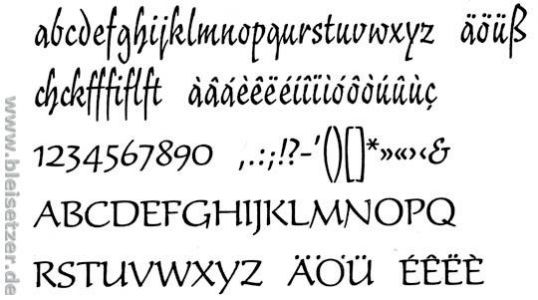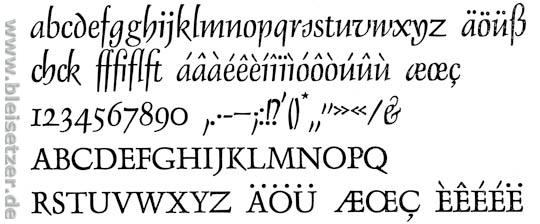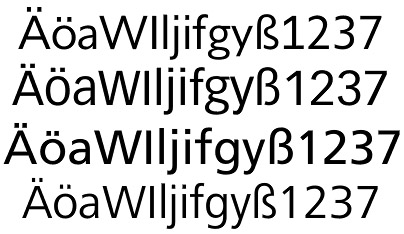
Schriftklau beim Design
Ich hatte erst überlegt, mich im Schriftpiraterie-Thread zu beteiligen, aber dieser Aspekt verdient meiner Meinung nach einen eigenen Thread. Es geht mir darum, dass viele Schriftarten offensichtlich direkt von einer anderen Schriftart abgeleitet sind, und ihr nicht etwa nur zufällig ähnlich sehen. Leicht verändert werden sie dann als neues Produkt deklariert. Ich möchte nur mal ein paar zufällig herausgesuchte Beispiele nennen (es gibt sie zuhauf):
Envoy (Minion)
Tyrnavia (Janson)
Gf H2O (Frutiger)
Bei anderen Shops findet man sicherlich ähnliche Beispiele.
Unter den Beispielen können natürlich hin und wieder welche sein, die nur unter anderem Namen vertrieben werden (wie Nimbus Sans für Helvetica). Die Segoe ist da wohl nur so umstritten, weil sie eben durch ihre Verwendung herausragt. Ansonsten scheint mir so etwas hundert-, wenn nicht tausendfach betrieben zu werden.
Bei diesem Thema bitte sehr, sehr vorsichtig sein! Die Beispiele sind nicht gut.
Allzu oft wird schnell gesagt, der hat mein Design, meine Idee "geklaut". Besser wäre wohl, dieser oder jener hat ebenfalls den selben Ansatz aufgegriffen bzw. weiterentwicklet bzw. seine Interpretation angefertigt. Alle Schriftentwerfer stehen auf den Schultern der Ahnen. Ein neues Design kann nur 25 Jahre geschützt werden, und zwar als Geschmacksmuster beim Patentamt. Von der praktischen Druchsetzbarkeit brauchen wir nicht zu sprechen, die geht fast gegen Null.
Es steht also jedem frei eine neue Version einer älteren oder gar historischen Schrift wie Janson, Kiss, Garamond und Co. zu versuchen, solange man keine schon digitale Schrift als Grundlage nutzt, also alles selber zeichnet.
Es ist schon merkwürdig wieviele Entwerfer (GGL, Spiekermann, Karl Heinz Lange, Georg Salden, Weidemann) in der einen oder anderen Situation freimütig damit koketieren, daß dieser oder jener ihrer verehrten Kollegen "ihre" Idee benutzt hätten. Das scheint zum etablierten Standesgeklapper zu gehören. :-)
Vom Schriftenklau im eigentlichen Sinne können wir sprechen, wenn große Firmen schon digitale Schriften nutzen und diese geringfügig abändern und das gar nicht einmal mit viel Mühe und dieses als "ihre Hausschrift" vorstellen um die Lizenzgebühren zu sparen. Die bekannten Fälle kann jeder auf Typophil oder im Fontblog nachlesen. Und trotz Offensichtlichkeit und öffentlicher Brandmarkung beleiben diese Dinge oftmals ungestraft, da diese Firmen einfach zu groß sind. Yves Peters hat sich auf dieses Gebiet spezialisiert und sammelt solche Fälle.
Von "Innovation" war hier nicht die Rede, sondern von Diebstahl! Ein Produkt muß nicht innovativ sein, um erfolgreich zu sein. Oftmals sind es nicht die Pioniere, die den Erfolg einstreichen, sondern die Nachfolger.
Futura ist kein gutes Beispiel, es war wohl die einzige Schrift die gerichtlich als Kunstwerk eingestuft wurde. Aber da müßte ich noch einmal nachlesen.
Nehmen wir mal eine andere Schrift, die Kabel von Rudolf Koch zum Beispiel. Wirklich jeder kann heute seine eigene Version davon erstellen und anbieten, solange er keine fremden Vorlagen nutzt und alles selber zeichnet und solange er keine Markenrechte, in dem Fall die Marke "Kabel" verletzt. Dies ist völlig legitim und rechtlich ok.
Die Moral lasse ich hier mal außen vor, das ist ein anderes, wenn nicht minder wichtiges Feld. Mein Tip: Bitte keine Schriften von noch lebenden Personen ohne deren schriftliche Einwilligung antasten. Ansonsten kann man vieles probieren, sollte sich aber immer seiner Verantwortung bewußt sein und sein Können richtig einschätzen. Sonst fällt es nur negativ auf die eigene Person zurück.
Es steht also jedem frei eine neue Version einer älteren oder gar historischen Schrift wie Janson, Kiss, Garamond und Co. zu versuchen, solange man keine schon digitale Schrift als Grundlage nutzt, also alles selber zeichnet.
Diese Ansicht kann ich ganz und gar nicht teilen. Mir geht es um den Unterschied zwischen
- dem Aufnehmen einzelner Merkmale einer Schrift und
- dem Abändern einer Schrift.
Ersteres ist glaube ich selbstverständlich, da niemand im luftleeren Raum lebt und Schriften gestaltet, und durch vergangene Schriften auch Konventionen geprägt werden, nach denen sich spätere Entwickler richten können/müssen.
Bei letzterem behält man die meisten Merkmale einer Schrift und profitiert weiterhin davon. Das, was von der alten Schriftart bleibt, ist mehr als nur ein gestalterischer Ansatz, es ist ein vollständiges Schriftdesign mit einer Persönlichkeit. Diese ist immer noch eindeutig erkennbar und kann der alten Ausgangsschrift zugeordnet werden. Im günstigsten Falle müsste man doch bei einem Klassiker nur hie und da leichte Veränderungen vornehmen, und hat immer noch eine hervorragende Schrift, nur mit neuem Namen. Ob diese Schrift dann direkt im Computer abgeändert wurde oder nach Vorlage abgezeichnet, ist für mich nur eine rechtliche Formalität. Schließlich kann sich jeder ein Schriftmuster ausdrucken und abpausen, und schon hat er eine Schrift angeblich nicht mehr direkt verändert.
Eine bestehende Schriftart zu verändern/zu verbessern ist ja in Ordnung (wie die tausendfache Interpretation von »Autumn leaves« im Jazz). Aber solange eine Schriftart ganz offensichtlich die meisten Merkmale der Vorgängerschrift beibehalten hat und eben nicht von Grund auf neu gezeichnet ist, sollte es auch erkennbar sein (»Neue Helvetica«), ebenso wie der Autor der Ausgangsschrift. Das ist deshalb berechtigt, weil die Ausgangsschrift immer noch wesentlich die Gestalt der neuen Schrift ausmacht.
Jeder Profi erkennt darin auf der ersten Blick die FF Confidential:
»Markenware« wird immer gefälscht werden. Ob nun Lacoste-T-Shirts aus der Türkei oder Fonts.
xbandrough ist ja wirklich schamlos, jeder Mikrometer ist so was von offentsichtlich abgekupfert - da hätte man doch besser seine Kinderdruckerei eingescannt ...